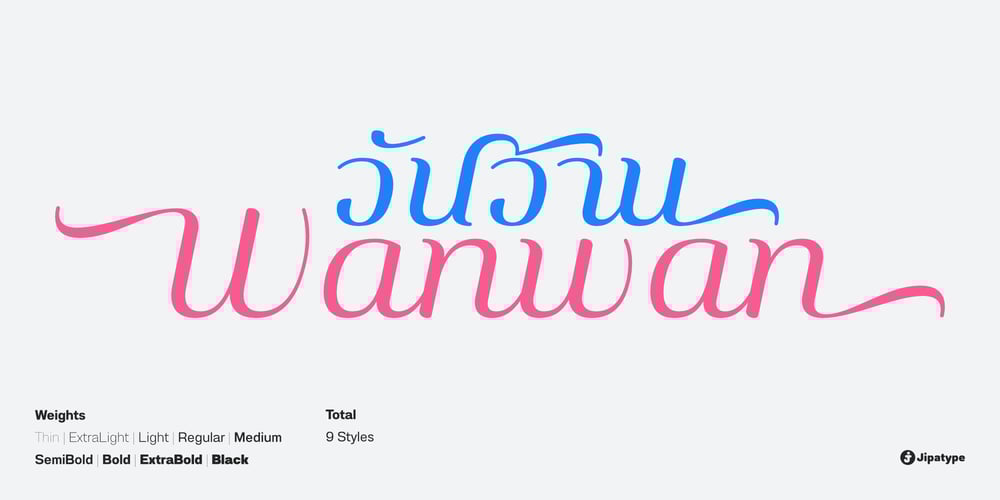
Wanwan
Wanwan font
Wanwan Font Family was designed by Anupap Jaichumnan and published by Jipatype. Wanwan contains 9 styles and family package options. ฟอนต์วันวาน อักษรแบบตัวเขียนอ้างอิงจากสไตล์การเขียนแบบพู่กันให้ความรู้สึกพริ้วไหว มีสไตล์ให้เลือกใช้ 9 สไตล์ตเป็นตัวเอียงทั้งหมด และเพิ่มความน่าสนใจด้วยการไฮไลท์ตัวอักษรที่ต้องการจากนั้นเปิดใช้งาน Stylistic Set 01-09 (ss01-09) หรือ Access All Alternates (aalt) จะมีป็อปอัพเด่งขึ้นมาให้เลือกอักษรทางเลือกอื่นๆ ฟอนต์วันวาน เหมาะสำหรับการผาดหัว ข้อความสั่นๆ หรือจัดวางเป็นกลุ่มคำสั่นๆ-Wanwan, a calligraphy font based on a brush writing style. There are 9 styles with italic. Comes with Stylistic Set 01-09 (ss01-09) or Access All Alternates (aalt). Wanwan suitable for headline wedding cards and other graphic work.